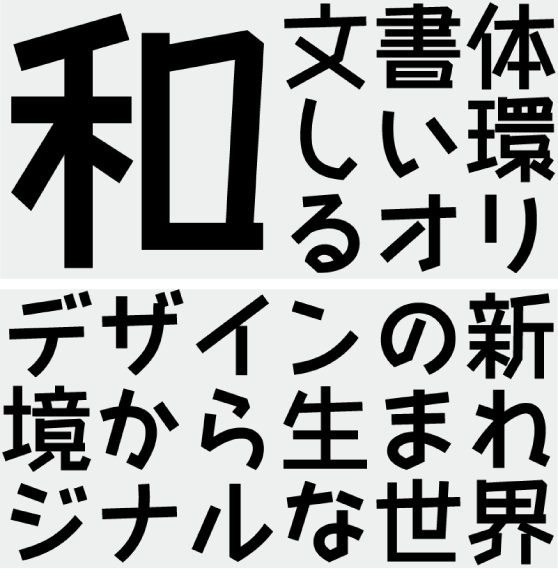
POP体
ウェブフォントジャパン株式会社
F1000-ヤンチャゴ J1p Regular (Takayuki Kuwahara)
F1000-yanchaGJ1p-Regular
直線を多用したメチャ元気で明るい書体。
JIS第一水準(2,965文字)までを収録・ひらがな・カタカナ・アルファベット・数字・記号